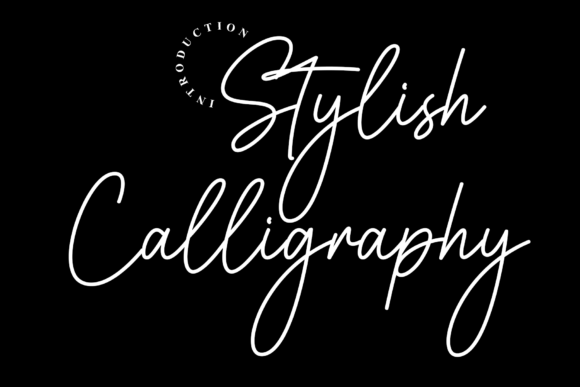
Stylish Calligraphy
Ulasan Stylistic Calligraphy – La Police d’Écriture qui Sublime le Luxe
Si vous cherchez une typographie qui marie élégance et fluidité, Stylish Calligraphy est la réponse. Conçue pour capturer l’essence d’un style moderne et sophistiqué, cette police manuscrite se transforme instantanément en un atout visuel incontournable pour tout projet haut de gamme.
Pourquoi choisir Stylish Calligraphy ?
- Aspect luxueux : Les courbes raffinées et les traits délicats évoquent immédiatement le prestige, idéal pour les invitations de mariage chic.
- Polyvalence événementielle : Parfaite pour le branding d’événements intimes – de petites soirées privées aux galas exclusifs.
- Signature éditoriale haut de gamme : Ajoute une touche d’authenticité aux magazines, livres d’art et rapports de mode.
- Superposition photographique : S’intègre harmonieusement sur des visuels lifestyle, renforçant le storytelling visuel.
- Lisibilité assurée : Malgré son allure manuscrite, chaque caractère reste clair, même en petite taille.
Applications concrètes
Utilisez Stylish Calligraphy pour créer des cartes d’invitation de mariage en or rose ou ivoire, des menus de réception, des logos d’événements privés, ou encore des citations inspirantes sur vos réseaux sociaux. Son rendu élégant augmente le taux de conversion et renforce la perception de qualité auprès de votre audience.
Verdict final
Stylish Calligraphy n’est pas seulement une police, c’est une déclaration de style. Que ce soit pour un mariage somptueux, une campagne publicitaire premium ou une galerie photographique raffinée, elle apporte une touche de sophistication qui distingue immédiatement votre création de la concurrence.